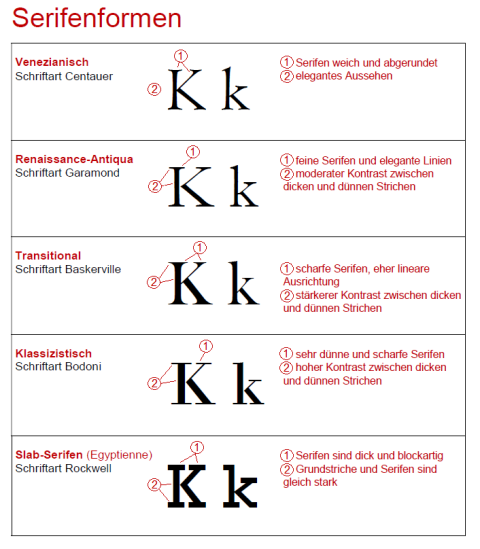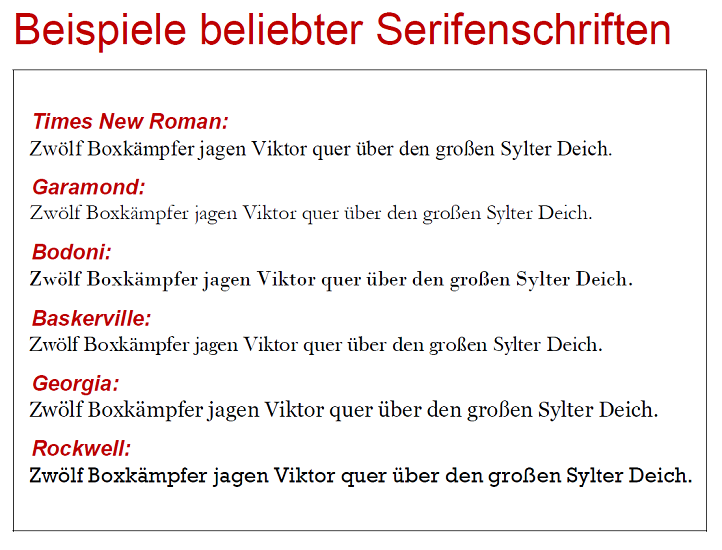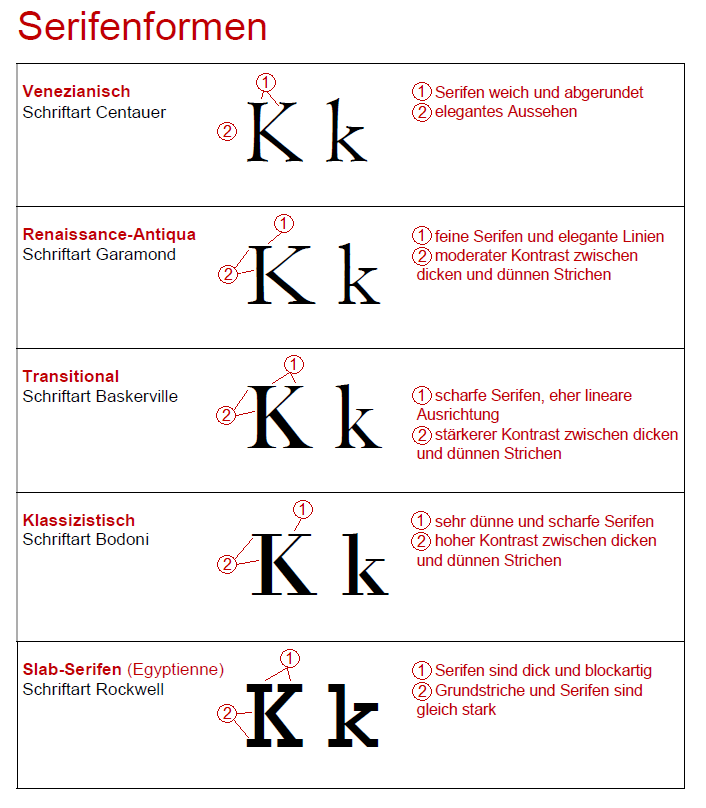
Einführung in serife Schriftarten
Was sind Serifen und Serifen-Schriftarten?
Serifen sind kleine dekorative Striche oder Linien (Füßchen) an den Enden der Hauptstriche von Buchstaben. Serifen Schriftarten, auch als Serifenschriften bekannt, nutzen diese Serifen, um den Buchstaben zusätzliche visuelle Komplexität zu verleihen und die Lesbarkeit von Texten zu verbessern. Serifen können verschiedene Formen annehmen, von zarten und geschwungenen Linien bis hin zu kräftigen und blockartigen Enden.
Geschichte der serifen Schriftarten
Die Geschichte der serifen Schriften reicht bis in die Antike zurück. Die ersten bekannten Beispiele stammen aus römischen Inschriften, wo die Serifen durch das Meißeln von Buchstaben in Stein entstanden. Diese frühen Serifen, auch als „Lapidarschriften“ bekannt, hatten eine praktische Funktion: Sie halfen, die Enden der Striche zu stabilisieren und Abplatzungen des Steins zu vermeiden. Mit der Erfindung des Buchdrucks durch Johannes Gutenberg im 15. Jahrhundert begannen eine systematische Entwicklung von serifen Schriftarten. Die Renaissance-Antiqua entstand, gefolgt von verschiedenen anderen Stilen im Laufe der Jahrhunderte, die die ästhetischen und technologischen Veränderungen ihrer Zeit widerspiegelten.
Nicht serife Schriftarten (Sans Serif Schriften)
Serifenfreie Schriftarten, auch als Sans Serif Schriften bekannt, verzichten auf diese dekorativen Elemente und bieten ein sauberes, modernes Erscheinungsbild. Bekannte Beispiele sind Arial, Helvetica und Calibri. Diese Schriftarten sind besonders gut für digitale Anwendungen und Bildschirmtexte geeignet, da sie bei niedrigen Auflösungen gut lesbar sind.
Art und Form der Serifen
Die Art und Form der Serifen variieren stark und verleihen jeder Serifenschrift ihren einzigartigen Charakter. Die wichtigsten Serifenarten sind:
- Venezianische Serifen: Diese Serifen sind weich und abgerundet, was ihnen ein klassisches und elegantes Aussehen verleiht. Beispiele hierfür sind die Schriftarten Jenson und Centauer.
- Renaissance-Antiqua: Diese Serifen haben einen moderaten Kontrast zwischen dicken und dünnen Strichen und weisen oft schräg angesetzte Serifen auf. Garamond ist ein prominentes Beispiel.
- Transitional: Serifen dieser Art haben einen stärkeren Kontrast und eine eher lineare Ausrichtung der Serifen. Baskerville gehört zu dieser Kategorie.
- Klassizistische Serifen: Diese Serifen sind scharf und dünn mit einem hohen Kontrast zwischen den Strichen. Bodoni und Didot sind typische Vertreter.
- Slab-Serifen: Auch als Egyptienne bekannt, haben diese Serifen dicke, blockartige Striche. Beispiele sind Rockwell und Courier.
Klassische Serifen-Schriftarten
Merkmale und Beispiele klassischer Serifenschriften
Klassische serife Schriftarten zeichnen sich durch ihre Eleganz und traditionelle Ästhetik aus. Zu den bekanntesten gehören:
- Times New Roman: Entwickelt 1931 für die Times of London, bekannt für ihre gute Lesbarkeit und den klassischen Stil.
- Garamond: Eine Schriftart aus dem 16. Jahrhundert, bekannt für ihre feinen und eleganten Linien.
- Baskerville: Im 18. Jahrhundert von John Baskerville entwickelt, bietet sie einen moderaten Kontrast und scharfe Serifen.
- Bodoni: Eine klassizistische Schriftart mit hohem Kontrast zwischen dicken und dünnen Strichen, bekannt für ihre elegante und markante Erscheinung.
Anwendungen und Bedeutung in der Typografie
Klassische serife Schriften sind aufgrund ihrer hervorragenden Lesbarkeit und ästhetischen Anziehungskraft weit verbreitet. Sie werden häufig in gedruckten Medien wie Büchern, Zeitungen und Zeitschriften verwendet. Diese Schriftarten sind ideal für lange Texte, da die Serifen den Lesefluss unterstützen und die Augen weniger anstrengen. Darüber hinaus verleihen sie Drucksachen eine seriöse und professionelle Ausstrahlung, was sie zur bevorzugten Wahl für offizielle Dokumente und literarische Werke macht.
Übergang zu modernen serifen Schriftarten
Entwicklung und Einflüsse
Der Übergang zu modernen serifen Schriftarten begann im späten 18. und frühen 19. Jahrhundert, als sich die Typografie weiterentwickelte und neue ästhetische und funktionale Anforderungen stellte. Die Entwicklung moderner Technologien und Drucktechniken hatte einen erheblichen Einfluss auf das Design von Schriftarten. Der Einsatz von Kupferstichen und später von digitalen Schriftdesigns ermöglichte eine präzisere Gestaltung und größere Vielfalt an Formen.
Unterschiedliche Epochen und ihre typischen Merkmale
- Transitional Serifenschriften: Diese Schriften, wie Baskerville, überbrücken den Stilwechsel von der alten Renaissance-Antiqua zur klassizistischen Antiqua. Sie haben einen stärkeren Kontrast zwischen dicken und dünnen Strichen und eine eher lineare Ausrichtung der Serifen.
- Klassizistische Serifenschriften: Schriftarten wie Bodoni und Didot zeichnen sich durch sehr dünne Serifen und einen hohen Kontrast zwischen den Strichen aus. Sie vermitteln eine starke visuelle Präsenz und Eleganz.
- Slab-Serifen (Egyptienne): Diese Schriftarten, wie Rockwell, haben dicke, blockartige Serifen und wurden im 19. Jahrhundert populär. Sie sind robust und auffällig, ideal für Überschriften und Plakate.